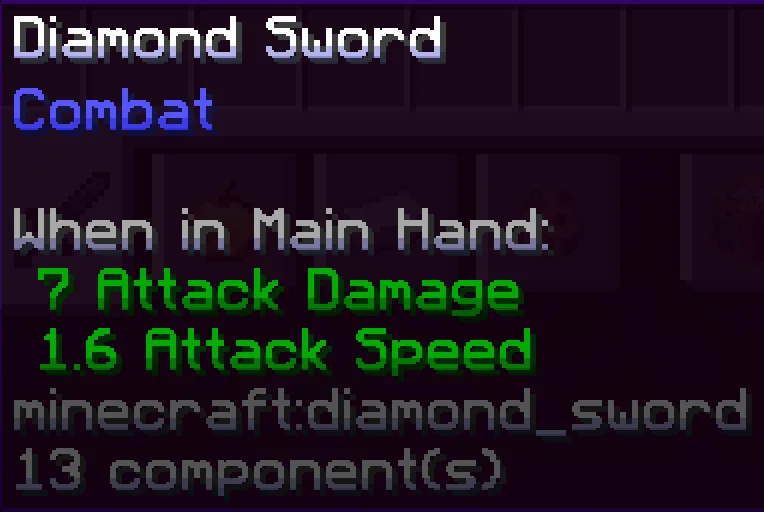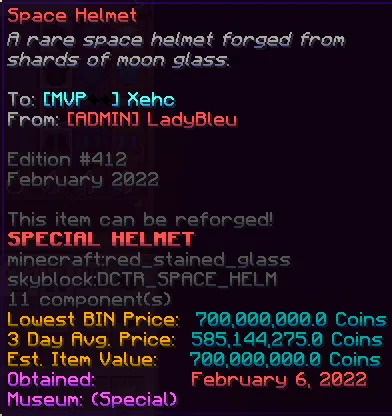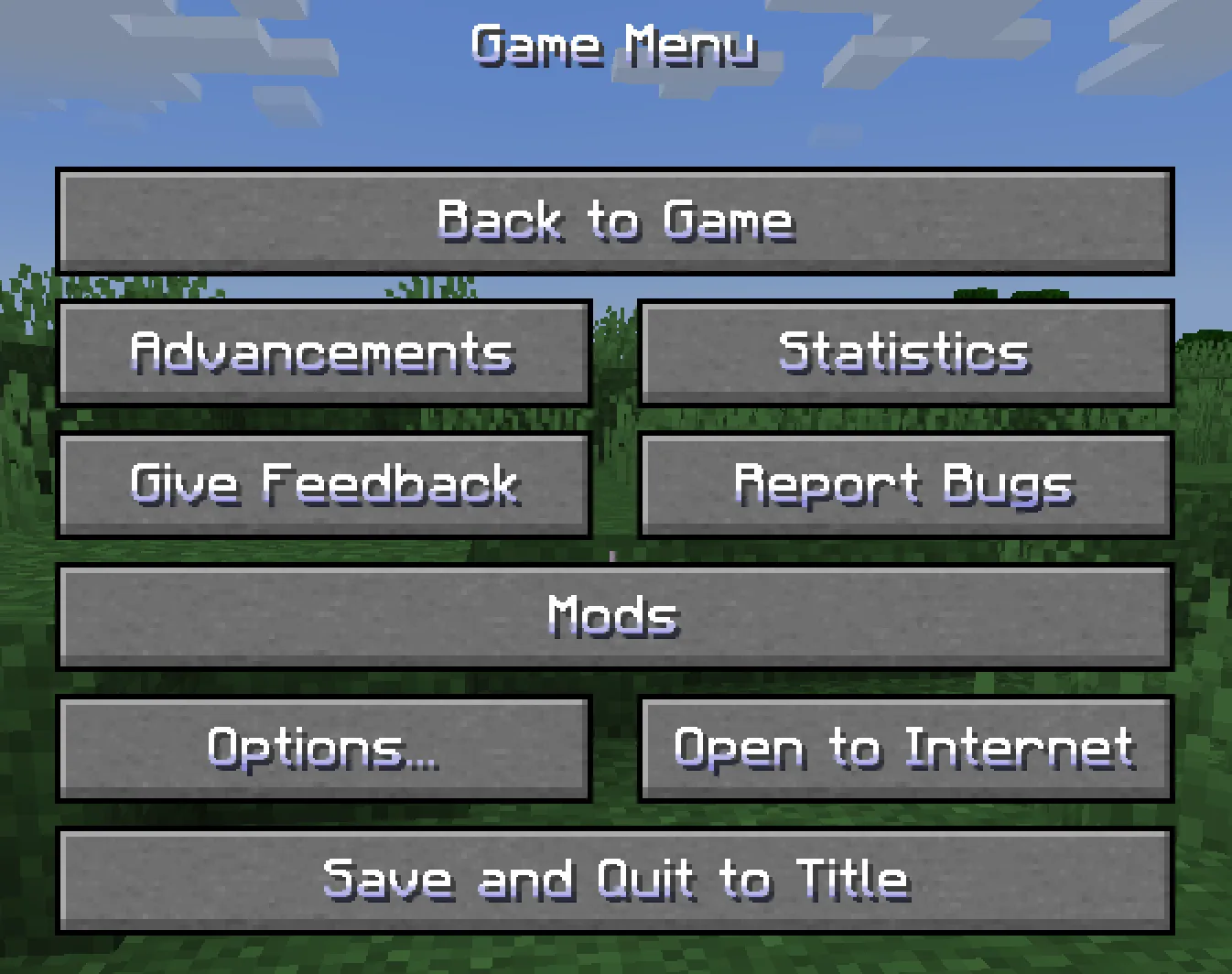
32x Smooth Shaded Font
Высокодетализированный гладкий шрифт для Minecraft с затенением. Основан на оригинальном "Smooth font - 32x" с элементами "Shaded font".
Этот ресурспак заменяет стандартный плоский шрифт Minecraft на гладкий 32x вариант с элементами затенения. Шрифт работает со всеми цветами текста в игре и сохраняет читаемость.
Ресурспак изменяет базовые английские символы и арабские цифры, делая их более объёмными и приятными для глаз. Более редкие символы получают только сглаживание без затенения.